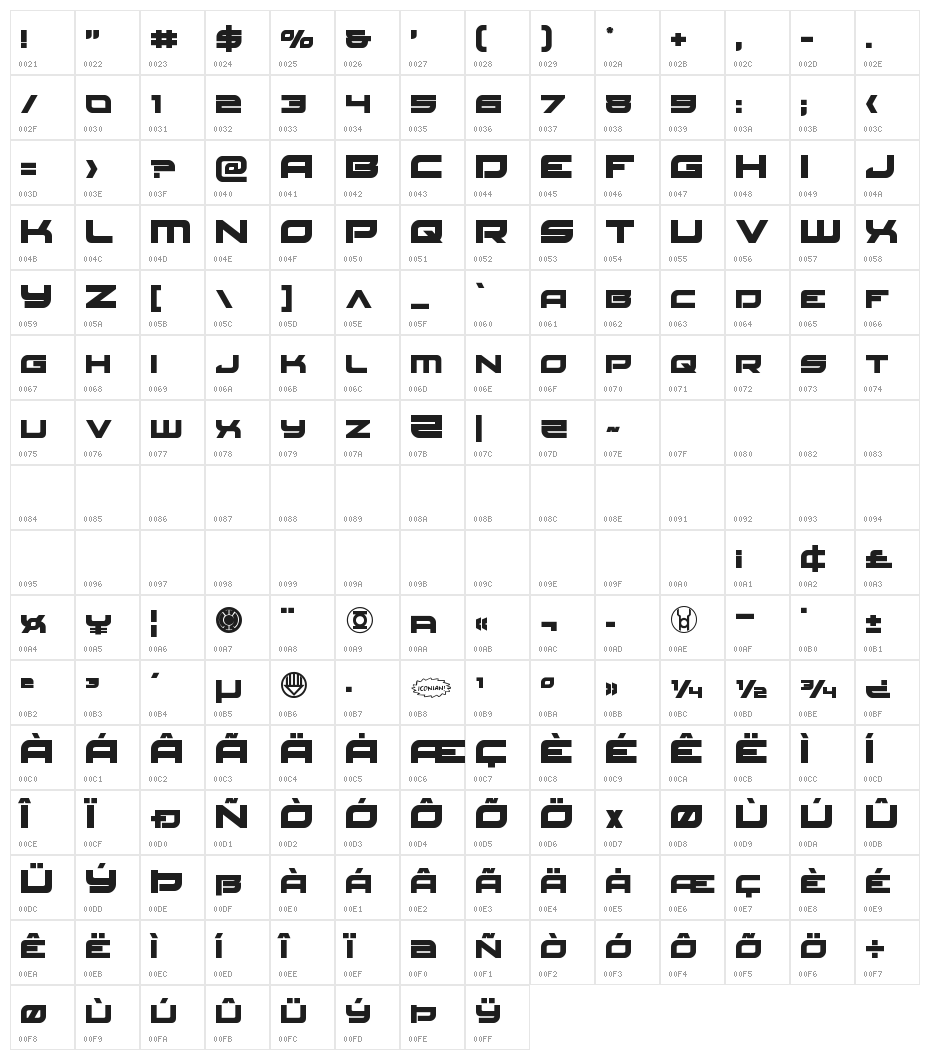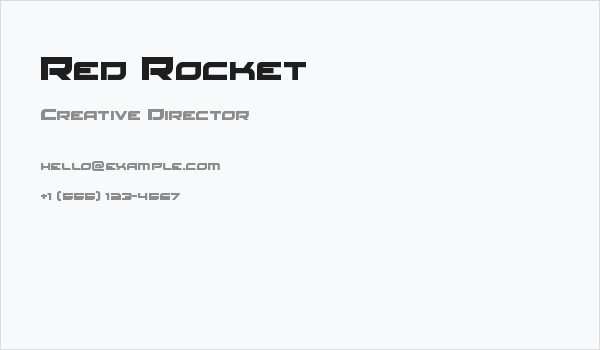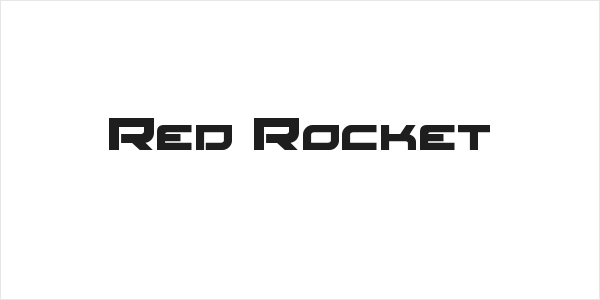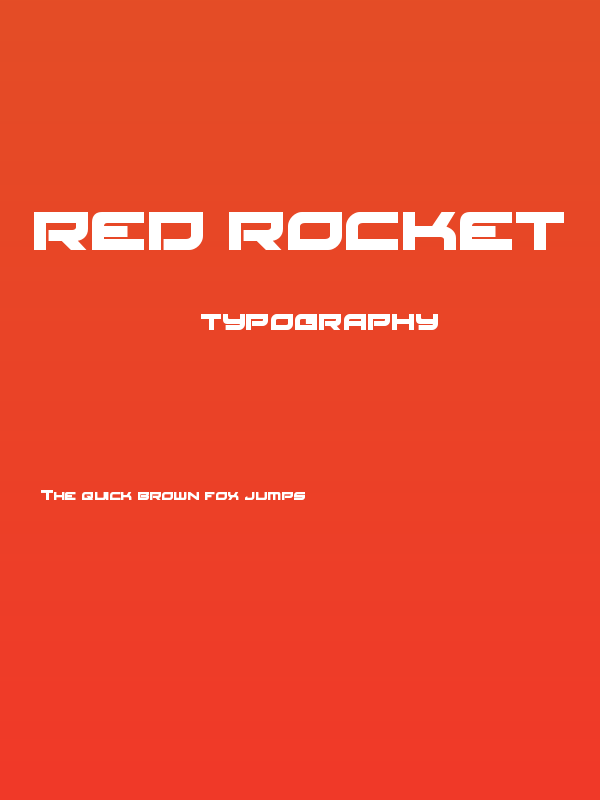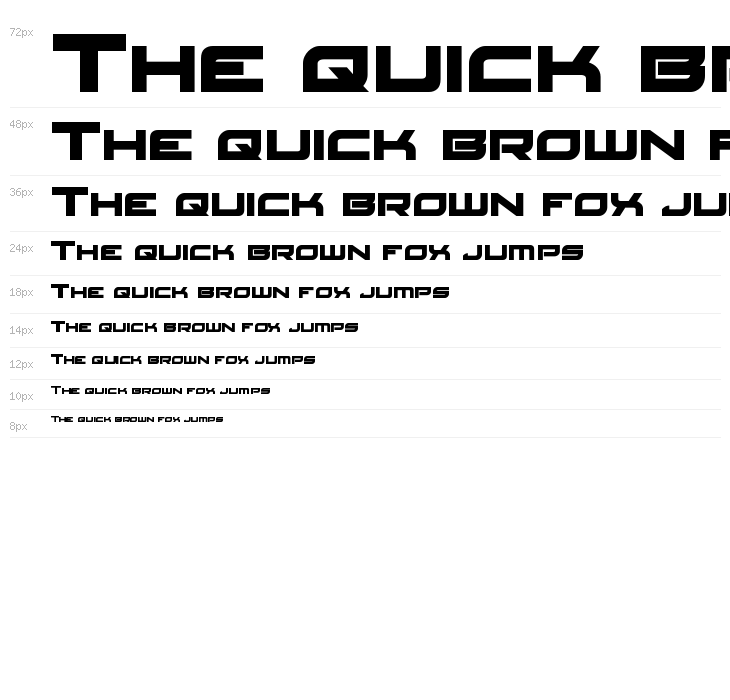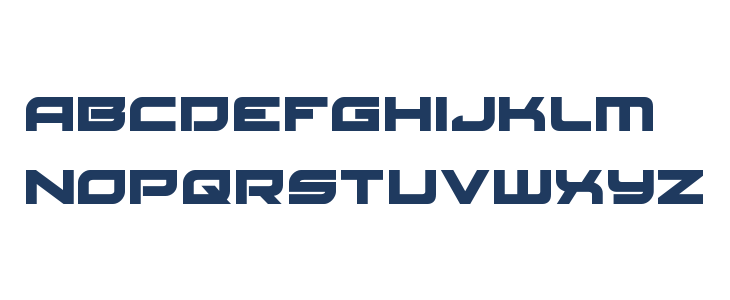
Red Rocket Font
✎ Futuristic
| Breite | Expanded |
| Vorgeschlagene Projekte | Ideal for technology branding, futuristic posters, video game titles, and modern advertising. |